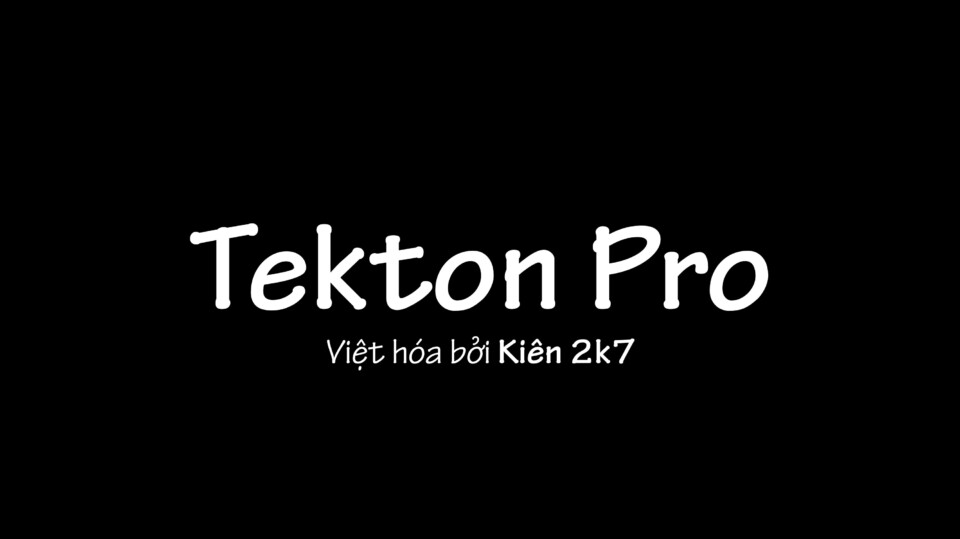
Giới thiệu về bộ Font việt hóa Tekton Pro
Trong thế giới thiết kế đồ họa, việc tìm kiếm một phông chữ vừa mang tính nghệ thuật vừa dễ đọc là điều vô cùng quan trọng. Font việt hóa Tekton Pro là một lựa chọn hoàn hảo được lấy cảm hứng từ những bản vẽ kiến trúc thủ công của kiến trúc sư người Mỹ Francis D.K. Ching. Đây là bộ Font Miễn Phí có phong cách viết tay phóng khoáng, hiện đại nhưng vẫn đảm bảo sự chuyên nghiệp cần thiết cho các dự án thiết kế tài liệu học tập hoặc thuyết trình tại trường học.
Đặc điểm nổi bật của Tekton Pro
Bộ phông chữ này sở hữu các đường nét thanh mảnh, mô phỏng lại nét bút mực trên giấy vẽ kỹ thuật, tạo cảm giác gần gũi và chân thực. Khi sử dụng phiên bản việt hóa, người dùng có thể hoàn toàn yên tâm về việc gõ dấu tiếng Việt mà không lo bị lỗi hiển thị hoặc mất ký tự. Điều này giúp các bạn học sinh dễ dàng trình bày bài báo tường, làm slide thuyết trình hoặc trang trí sổ tay cá nhân một cách sinh động nhất.
Cách sử dụng Font việt hóa Tekton Pro trong thiết kế
Để phát huy tối đa vẻ đẹp của phông chữ này, bạn nên kết hợp nó với các tông màu tối giản hoặc phong cách vintage. Font chữ này rất phù hợp cho các tiêu đề ngắn, các câu trích dẫn truyền cảm hứng hoặc dùng làm ghi chú trong các bản vẽ kỹ thuật cơ bản. Với cấu trúc chữ rõ ràng, nó giúp người xem dễ dàng nắm bắt nội dung mà không gây mỏi mắt.
Kết luận về bộ phông chữ kiến trúc